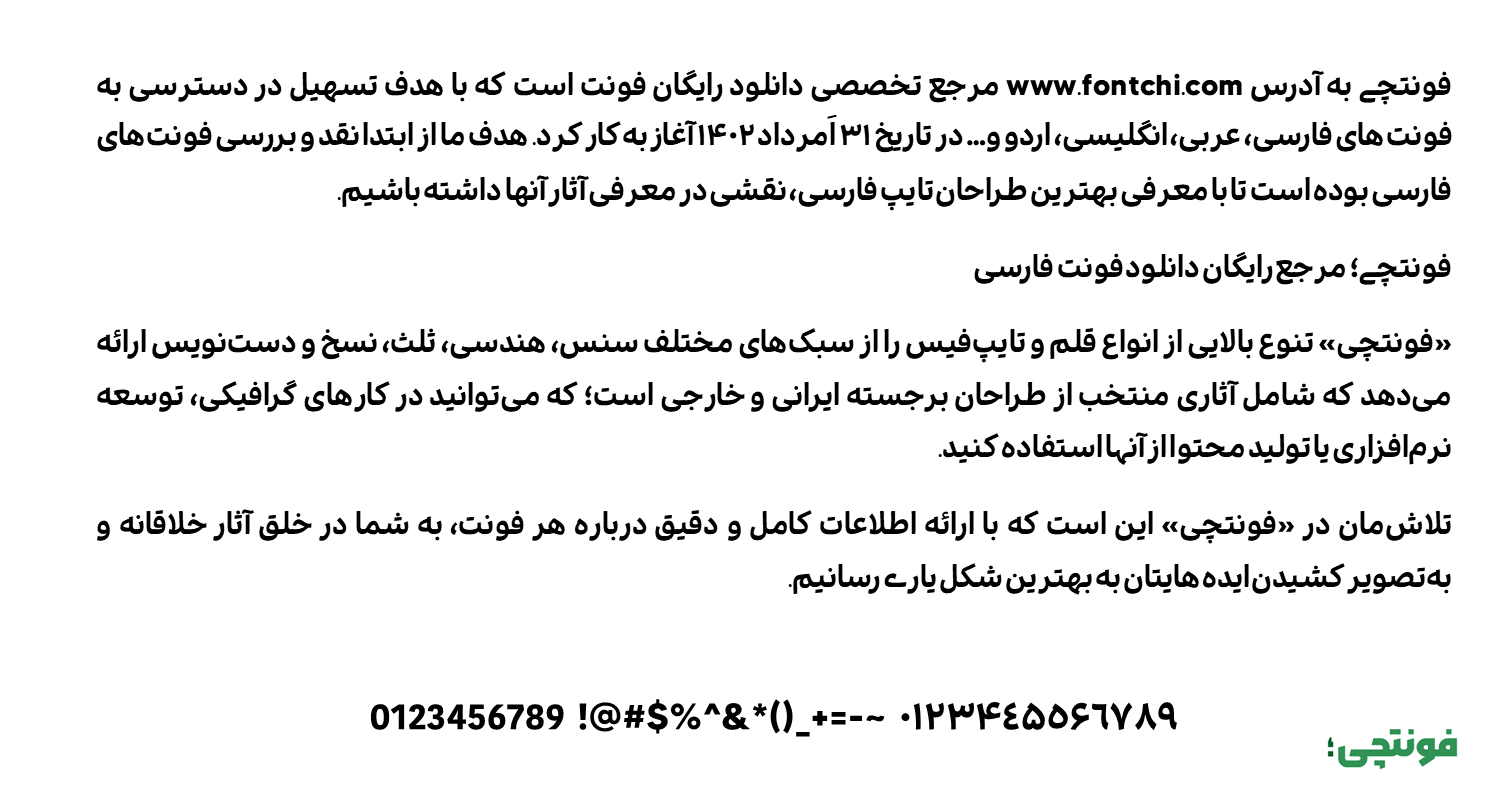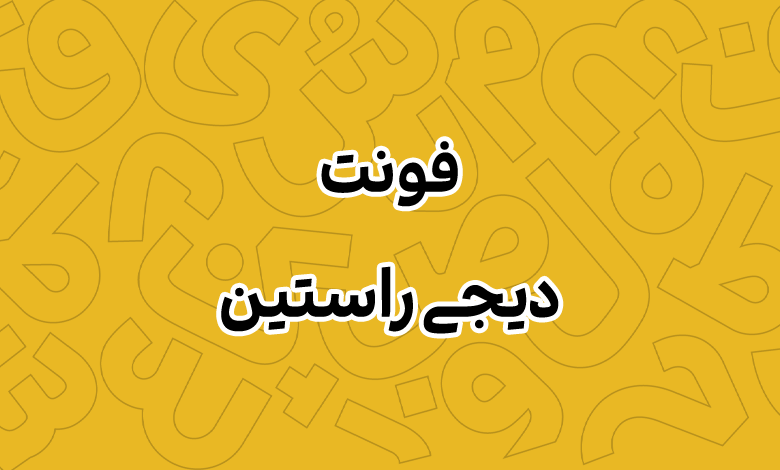
فونت راستین (Digi Rastin)
فونت راستین یا دیجی راستین (به انگلیسی: Digi Rastin) از فونتهای مدرن و محبوب فارسی است که توسط مجموعه دیجی فونت طراحی و ارائه شده است. این فونت با هدف ارائه یک قلم خوانا، زیبا و کاربردی برای استفاده در انواع پروژههای گرافیکی، متنی و دیجیتال طراحی شده که با وزن Bold و ضخیم خود کاربردهای متنوعی دارد.
طراحی دقیق نقطهها، پشتیبانی از حروف جایگزین «ه» و «ی»، خوانایی خوب و ساختار نمایشی به این فونت داده است. این ویژگی آن را برای متنهای طولانی، مانند مقالات، کتابها و محتوای وب، مناسب میکند. این قلم توسط مهدی برقگیر طراحی شده است.
بررسی و دانلود فونت دیجی راستین (Digi Rastin)
فونت راستین دارای کرنینگ حرفهای و اعرابگذاری هوشمند است که با رعایت فواصل بین حروف بهصورت متعادل و بدون تداخل، خوانایی خوبی به این قلم داده است. این فونت فارسی جدید که از زبانهای کوردی، عربی و انگلیسی هم پشتیبانی میکند برای پروژههای چندزبانه کاربردی است.
این فونت با شخصیتی پویا و جدی، هم برای آثار فانتزی و هم برای طرحهای رسمی قابل استفاده است. از تیترها و عناوین تبلیغاتی گرفته تا متنهای آموزشی و اینستاگرامی، دیجی راستین کاربرد گستردهای دارد.
فونت دیجی راستین با ظاهری مدرن و مینیمال، حس و حالی امروزی به طرحها میبخشد. این فونت بهویژه در شبکههای اجتماعی مانند اینستاگرام برای تولید محتوا بسیار مورد استقبال قرار گرفته است. از جمله مزایای این فونت عبارتند از:
- خوانایی و وضوح بالا: مناسب برای متنهای طولانی و سایزهای کوچک، حتی در محیطهای دیجیتال.
- چندمنظوره بودن: قابلیت استفاده در طرحهای رسمی، فانتزی و تبلیغاتی.
- امکانات خوب: قابلیت استفاده از حروف جایگزین برای نمایشیتر کردن ظاهر فونت.
- استفاده ترکیبی از نقاط: نقاط این فونت به صورت ترکیبی شامل نقاط خطی و دایرهای پیوسته و منفصل است.
این فونت دارای سبک سنس است که از جمله دیگر فونتهای محبوب در این زمینه میتوان به ایران سنس و یکان بخ اشاره کرد.
راستین در مقایسه با فونت ایران سنس از یک وزن بولد پشتیبانی میکند در حالی که ایران سنس یک فونت حرفهای با تنواع وزنی بسیار بالاست که دارای نسخه وریبل نیز میباشد. همچنین امکانات حرفهایتری در این فونت وجود دارد. اما اگر دنبال فونت رایگان مشابه ایران سنس باشید، فونت راستین بولد میتواند جایگزین مناسبی باشد.
فونت یکان بخ نیز ظاهری نزدیک به همین قلم دارد با این تفاوت که با هندسه و کمی خط نسخ ترکیب شده است و برای استفاده در پروژههایی با تنوع بالاتر قابل استفاده است.